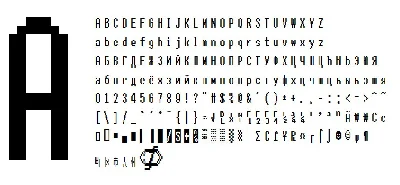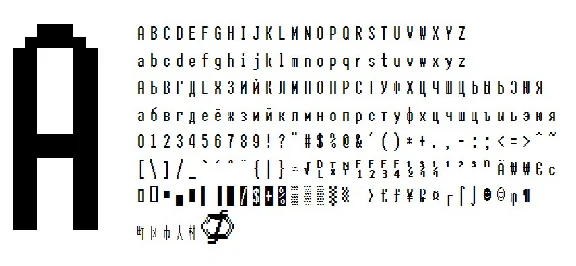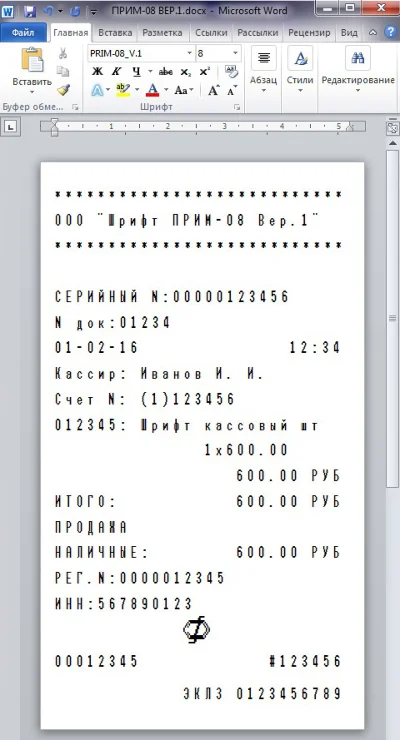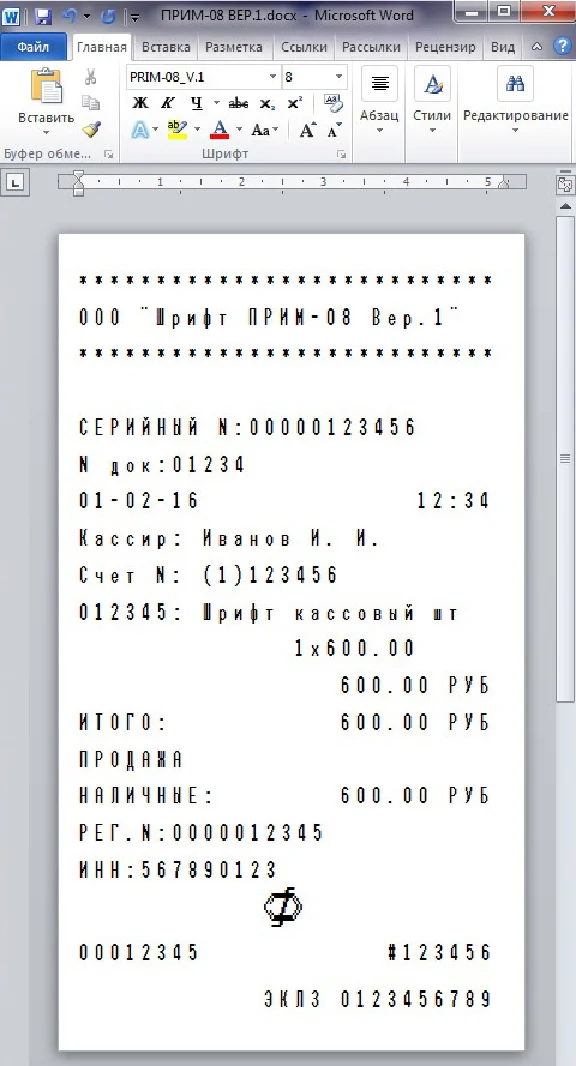
Шрифт ККМ ПРИМ-08 вер.1 (ttf)
Шрифт фискального регистратора ПРИМ-08 вер.1 в формате TTF (русские и английские буквы) для использования в программе Microsoft Word. В архиве находятся шрифт в формате TTF и шаблон чека. Вам остается только установить шрифт в систему (обычно C:\WINDOWS\Fonts), открыть шаблон и начать редактирование. Печатать чеки предпочтительно на термопринтере, на кассовой термоленте. Хотя можно печатать и на струйнике и лазерном, с возможностью вывода на факсовую бумагу. Лучшее качество, естественно, при печати на термопринтерах.